24 najlepsze czcionki skryptowe 2023 r. (bezpłatne i premium)
Opublikowany: 2023-04-20Chcesz dodać odrobinę elegancji i wyrafinowania swoim projektom? Czy chcesz, aby Twój tekst wyróżniał się pięknymi i stylowymi czcionkami skryptowymi? Nie szukaj dalej, ponieważ mamy dla Ciebie listę 24 najlepszych dostępnych obecnie czcionek skryptowych.
Ten post na blogu zawiera starannie dobrany wybór czcionek skryptowych, które idealnie nadają się do różnych zastosowań projektowych, takich jak zaproszenia ślubne, branding, logo, grafika w mediach społecznościowych i nie tylko.
Przy ponad 130 000 czcionek dostępnych na różnych stronach internetowych wybór właściwej może być przytłaczający. Dlatego zawęziliśmy najlepsze opcje, które pomogą Ci zaoszczędzić czas i wysiłek.
W tym artykule szczegółowo omówimy 24 najlepsze czcionki skryptowe, w tym ich unikalne funkcje, style i odpowiednie zastosowania. Niezależnie od tego, czy jesteś profesjonalnym projektantem, czy entuzjastą-amatorem, ten przewodnik dostarczy Ci cennych informacji i inspiracji do następnego projektu.
Zanurzmy się więc w świat pięknych czcionek skryptowych!
Najlepsze czcionki skryptowe premium
Zaprezentujemy niektóre z najpopularniejszych i najwyżej ocenianych obecnie dostępnych czcionek skryptowych premium, wraz z ich unikalnymi funkcjami i zaletami.
Niezależnie od tego, czy jesteś profesjonalnym projektantem, czy dopiero zaczynasz, w tym artykule znajdziesz coś dla każdego, kto chce przenieść swoją grę w projektowanie na wyższy poziom. Zanurzmy się więc i odkryjmy najlepsze czcionki skryptowe premium!
Skrypt Bagietka
Baguet Script to nowoczesna czcionka pisma pędzla, która zapewnia miękki i przyjazny akcent Twoim projektom. Jest wyposażony w dwa zestawy wielkich liter, jeden bardziej subtelny, a drugi bardziej efektowny, co pozwala wybrać odpowiednią opcję zgodnie z własnymi preferencjami.
Ta czcionka oferuje również trzy różne rodzaje pasujących początkowych i końcowych znaków kaligraficznych dla małych liter oraz wiele opcji dla wznoszących się i opadających, co daje szeroki zakres opcji do wyboru.
Dzięki swojej wszechstronności i elastyczności Baguet Script jest idealny dla projektantów, którzy szukają miękkiego, nowoczesnego skryptu z wieloma opcjami dostosowywania. Jeśli więc chcesz nadać swojemu projektowi świeży i przyjemny charakter, Baguet Script jest idealnym wyborem.
Skrypt Octavii
Octavia Script to jedna z nowoczesnych czcionek Script, która łączy style klasyczne i współczesne. Ta czcionka ma wiele funkcji, które wyróżniają ją spośród innych.
Octavia Script ma alternatywy kontekstowe, ligatury uznaniowe, alternatywy stylistyczne oraz formy początkowe i końcowe. Ustawienie dla formularzy początkowych i końcowych jest kontekstowe, co ułatwia ich wyłączenie w razie potrzeby. Domyślnym ustawieniem czcionki jest włączenie formy początkowej i końcowej.
Użycie alternatyw kontekstowych oznacza, że Octavia Script może automatycznie przełączać się między różnymi formami liter w oparciu o ich położenie w tekście. Daje to naturalny i płynny wygląd, jak gdyby tekst był napisany odręcznie.
Stuscrpt
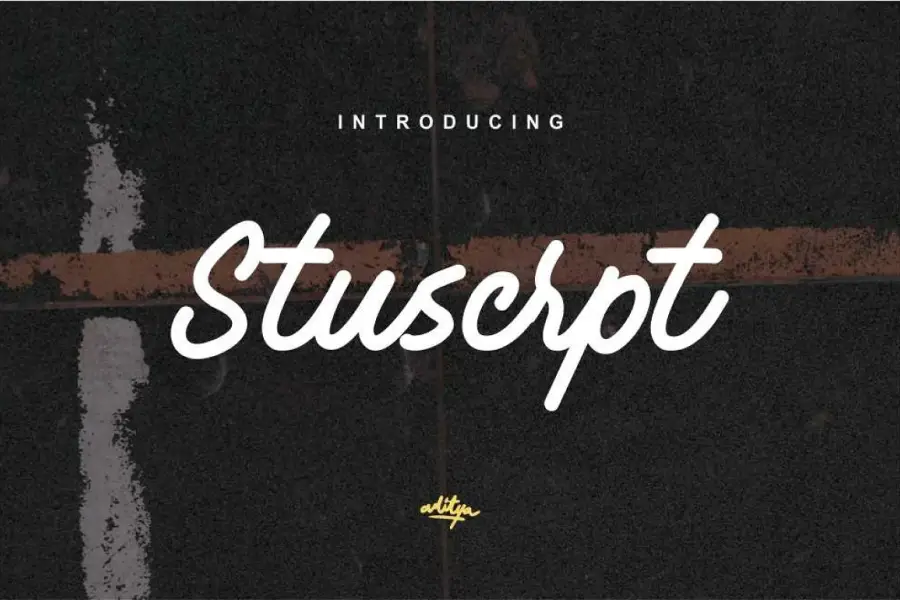
Stuscrpt to nowoczesna czcionka skryptowa, która została wydana w 2020 roku. Ta czcionka może być używana w różnych aplikacjach, takich jak typografia, fotografia i logo. Jego unikalny styl sprawia, że idealnie nadaje się do dodania elegancji Twoim projektom.
Jedną z wyróżniających cech Stuscrpt jest jego wszechstronność. Niezależnie od tego, czy projektujesz logo, czy tworzysz układ typograficzny, ta czcionka z pewnością wyróżni Twoją pracę. Dodatkowo nowoczesny design czcionki gwarantuje, że pozostanie ona aktualna przez wiele lat.
Skrypt Moscato
Moscato Script to urocza i stylowa odręczna czcionka, która dodaje osobistego charakteru każdemu projektowi. Ta czcionka jest wszechstronna i może być używana do różnych zastosowań, takich jak cytaty, plakaty, materiały ślubne, projekty modowe, logo, zaproszenia, artykuły papiernicze i wiele innych.
Unikalne cechy Moscato Script sprawiają, że wyróżnia się on spośród innych czcionek. Ręcznie rysowany wzór nadaje mu naturalny i organiczny charakter, który dodaje charakteru i osobowości Twojej pracy. Jego czyste linie i gładkie krzywe ułatwiają czytanie i doskonale nadają się do dodania odrobiny elegancji do każdego projektu.
Jedną z najlepszych rzeczy w Moscato Script jest jego wszechstronność. Może być używany do szerokiej gamy projektów, od codziennych po oficjalne. Niezależnie od tego, czy projektujesz zaproszenie na ślub przyjaciela, czy tworzysz logo dla nowego przedsięwzięcia biznesowego, Moscato Script sprosta temu zadaniu.
Atakana
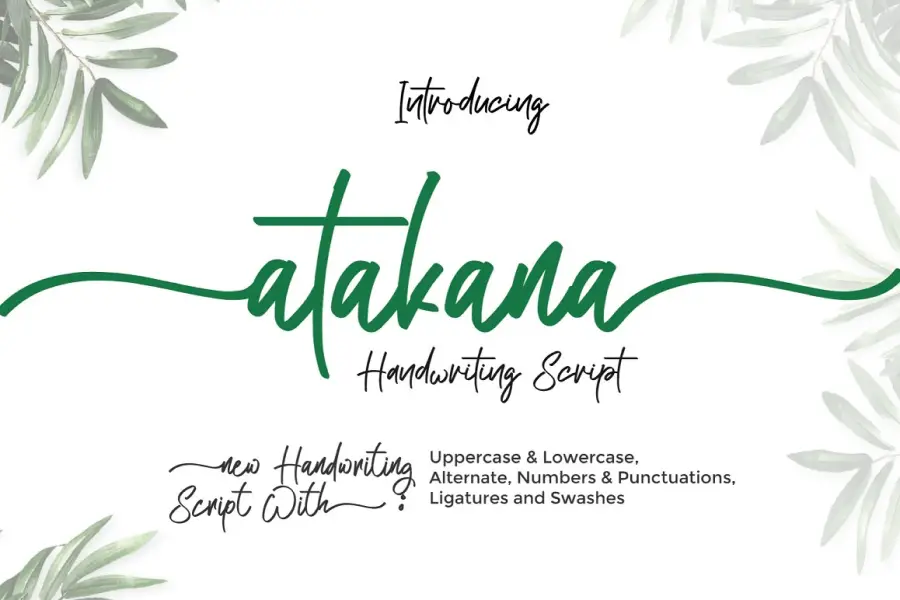
Atakana Script to piękna nowa czcionka pisma odręcznego, która została stworzona z miłością. Jest idealny do wszystkich Twoich potrzeb związanych z brandingiem, niezależnie od tego, czy chodzi o zaproszenia ślubne, romantyczne projekty, marki studyjne, logo, zaproszenia, posty w mediach społecznościowych, odzież, plakaty, znaki kawiarni/restauracji i wiele innych.
Czcionka zawiera eleganckie, wirujące litery, które wyglądają, jakby zostały napisane ręcznie. Jest łatwy do odczytania i dodaje unikalny akcent personalizacji do każdego projektu. Atakana Script nadaje się zarówno do użytku osobistego, jak i komercyjnego, dzięki czemu jest wszechstronną czcionką, której można używać do wszystkiego, od zaproszeń po reklamy.
Czcionka jest dostępna w wielu formatach plików, w tym OTF, TTF i WOFF. Oznacza to, że można go używać na różnych platformach i programach, co czyni go wygodnym wyborem dla projektantów, którzy muszą pracować na wielu urządzeniach.
Scenariusz domku dla ptaków
Skrypt ptaszarni to zachwycająca czcionka odręczna stworzona za pomocą markerów. ta czcionka jest idealna dla osób, które chcą tworzyć charakterystyczne znaki firmowe lub osobiste podpisy i czcionki skryptowe dla słów. zawiera duże standardowe znaki, znaki interpunkcyjne i obsługuje wiele języków.
Unikalny projekt Bird House script nadaje mu zabawny i naturalny charakter, który wyróżnia go spośród innych czcionek. jego ręcznie rysowany wygląd dodaje odrobinę osobowości każdemu projektowi, w którym jest używany. Niezależnie od tego, czy projektujesz logo, czy tworzysz stronę internetową, wszechstronność skryptu birdhouse gwarantuje, że można go używać w różnych ustawieniach.
Florentina
Florentina to czcionka, która może dodać charakteru i wyrafinowania Twoim projektom. Jego projekt skryptu jest idealny do tworzenia logo i brandingu, które wyróżnią się na tle konkurencji. Unikalna kolekcja symboli geometrycznych Florentiny jest również doskonałym dodatkiem do Twojego arsenału projektowego, umożliwiając łatwe tworzenie pięknych i przyciągających wzrok kompozycji.
Elegancki styl pisma czcionki zapewnia klasyczny, a jednocześnie nowoczesny styl, który z pewnością zrobi wrażenie. Jest idealny dla projektantów, którzy chcą dodać odrobinę luksusu do swoich prac, nie rezygnując z czytelności ani funkcjonalności. Niezależnie od tego, czy chodzi o druk, czy projekt cyfrowy, Florentina może przenieść Twoje projekty na wyższy poziom.
Góral
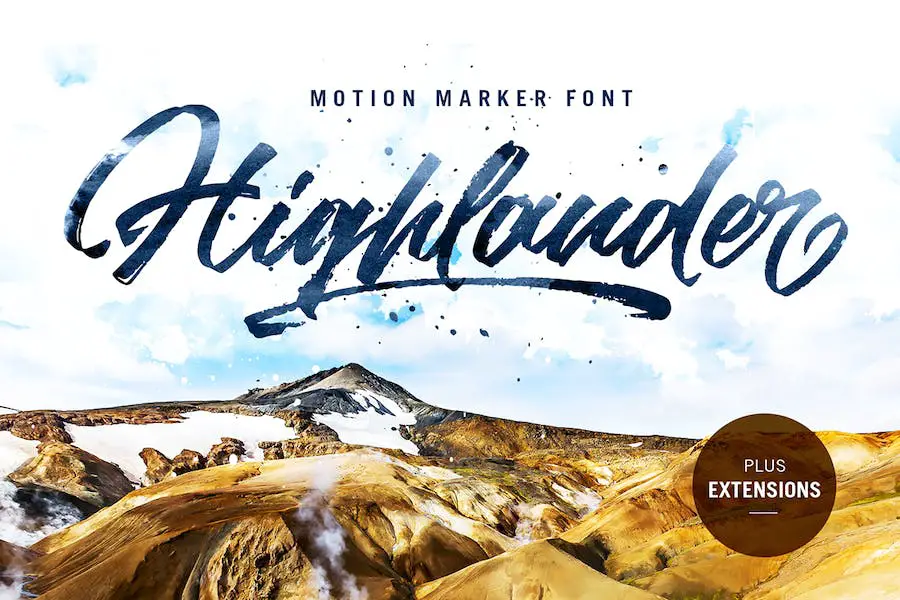
Highlander to obowiązkowa czcionka dla każdego projektanta, który chce tworzyć odręczne litery na zamówienie. Dzięki pełnemu zestawowi wielkich i małych liter ta czcionka zapewnia projektantom swobodę przekształcania tekstu w autentyczne, spersonalizowane dzieła sztuki.
Oprócz standardowych glifów Highlander zawiera również cyfry, znaki interpunkcyjne i obsługę wielu języków. Jako bonus projektanci otrzymają dodatkową czcionkę wypełnioną rozszerzeniami zaprojektowanymi tak, aby idealnie uzupełniały ich główny tekst. Jest również idealny do pogrubionych czcionek skryptowych.
Ogólnie rzecz biorąc, Highlander to doskonały wybór dla projektantów poszukujących wysokiej jakości, wszechstronnej czcionki, która przeniesie ich pracę na wyższy poziom. Niezależnie od tego, czy projektujesz logo, tworzysz plakat, czy projektujesz stronę internetową, zakres funkcji Highlandera sprawia, że jest to doskonała opcja dla wszelkiego rodzaju projektów projektowych.
Pentagon
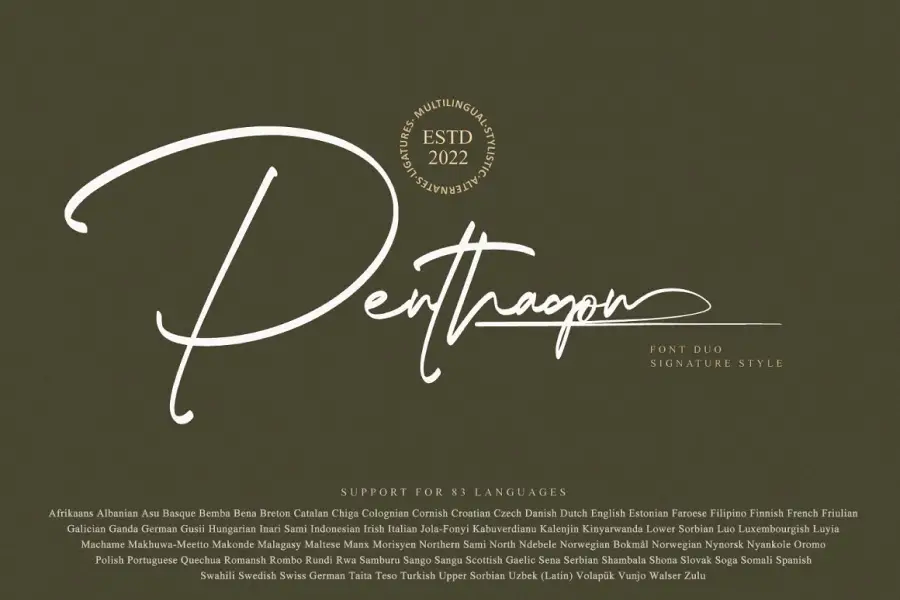
„Penthagon” to duet czcionek skryptowych, który może pomóc w nadaniu produktom biznesowym naturalnego i współczesnego charakteru. Ta elegancka i charakterystyczna czcionka jest idealna do tworzenia odręcznych logo, papeterii ślubnej, logo znaków wodnych fotografów, nowoczesnych stron internetowych, brandingu modowego, wizytówek, zaproszeń ślubnych i innych.
Luksusowy i wysokiej klasy wygląd „Penthagon” wyróżnia go spośród innych czcionek w swojej kategorii. Jego wszechstronność pozwala na wykorzystanie go do różnych projektów, zarówno do użytku osobistego, jak i komercyjnego. Płynne pociągnięcia i naturalne krzywizny każdej litery wydzielają lekką atmosferę, która jest idealna dla każdego projektu. Jest również kompatybilny ze skryptowymi czcionkami ślubnymi.
Skrypt Emelli
Emellie Script to unikalny krój kaligraficzny, który zawiera zabawne kobiece znaki kaligraficzne, dzięki czemu idealnie nadaje się do różnych projektów, takich jak logo, kartki okolicznościowe, materiały ślubne i inne. Ta czcionka zawiera standardowe znaki łacińskie, zamienniki wielkich liter, formy początkowe i końcowe, cyfry i symbole, rozszerzone znaki łacińskie i wybrane ligatury.
Jedną z wyróżniających cech Emellie Script jest jego wszechstronność. Może być używany w szerokiej gamie projektów, od eleganckich po figlarne, i we wszystkich pomiędzy. Początkowa i końcowa forma czcionki oraz wybrane ligatury dodają każdemu projektowi odrobinę personalizacji.
Kolejną wielką zaletą Emellie Script jest to, że zawiera czcionki internetowe. Ułatwia to włączenie czcionki do Twojej witryny, zapewniając spójność na wszystkich platformach.
Podpis rastrowy
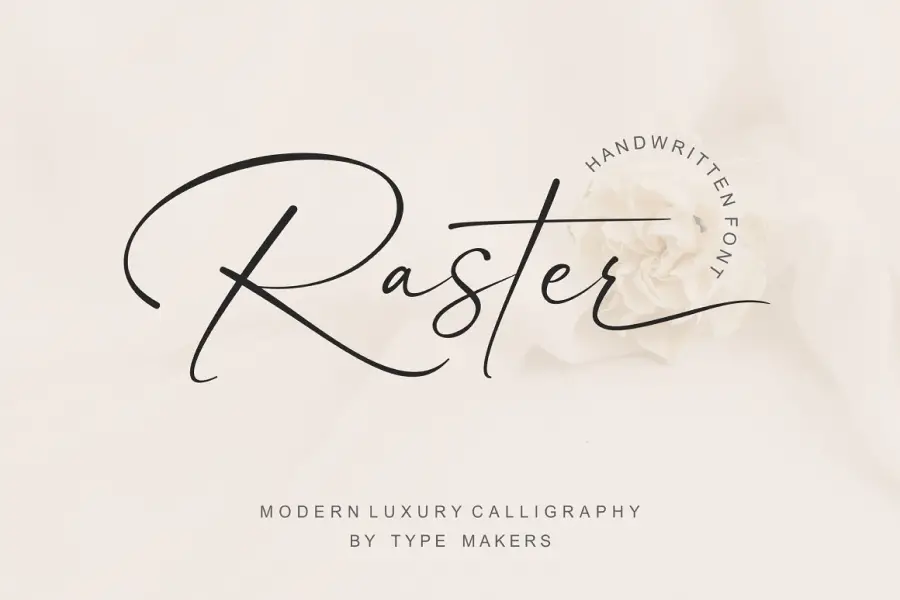
„Raster Signature” to urocza czcionka imitująca naturalne pismo odręczne. Ta czcionka jest idealna do dodawania osobistego charakteru do różnych projektów, w tym logo, zaproszeń, materiałów piśmiennych, projektów ślubnych, postów w mediach społecznościowych, reklam i opakowań produktów.
Dzięki nieregularnym pociągnięciom i delikatnym krzywiznom „Raster Signature” dodaje elegancji i ciepła każdemu projektowi. Ta czcionka jest idealna do tworzenia wyjątkowej i zapadającej w pamięć tożsamości marki, a także do dodawania osobistego charakteru specjalnym wydarzeniom.
Wszechstronność „Raster Signature” sprawia, że jest to doskonały wybór dla projektantów poszukujących czcionki, której można używać w różnych ustawieniach. Od fotograficznych znaków wodnych po etykiety produktów — naturalny urok tej czcionki z pewnością zrobi wrażenie.
Skrypt Rattfiny'ego
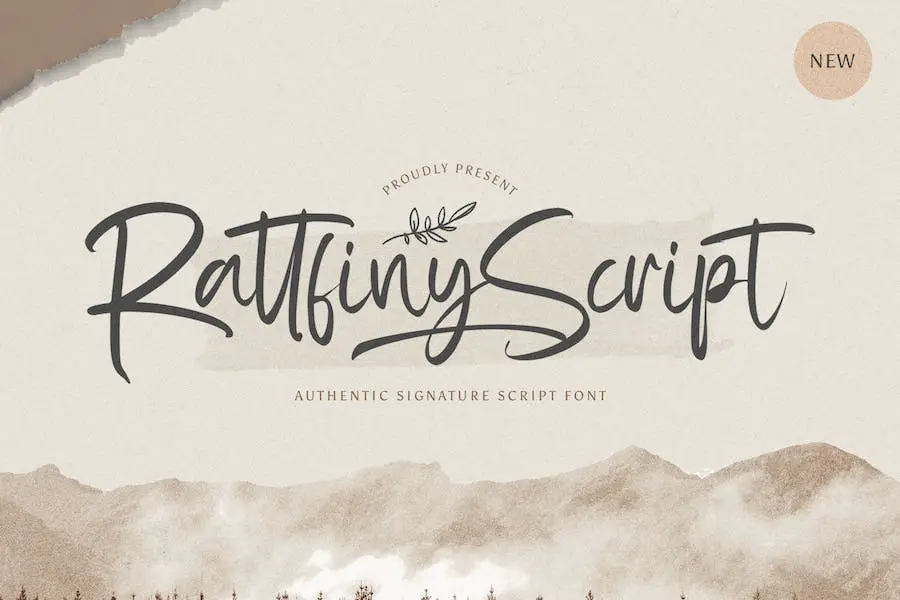
Rattfiny Script to znakomita odręczna czcionka emanująca elegancją i wdziękiem. Jego piękne, płynne postacie są dobrze wyważone, dzięki czemu idealnie pasują do szerokiej gamy projektów. Ta czcionka dodaje odrobinę wyrafinowania każdemu kreatywnemu projektowi, ożywiając go delikatnym stylem pisma.
Jedną z wyróżniających cech Rattfiny Script jest jego wszechstronność. Uzupełnia wiele różnych stylów projektowania, od zaproszeń ślubnych po materiały brandingowe, dzięki czemu jest cennym dodatkiem do każdej kolekcji czcionek. Jej pełne wdzięku krzywizny i skomplikowane detale nadają jej wyjątkowy charakter, który odróżnia ją od innych czcionek skryptowych dostępnych na rynku.
Kolejnym wspaniałym aspektem Rattfiny Script jest jego czytelność. Nawet przy delikatnym wyglądzie litery są łatwe do odczytania, dzięki czemu każda wiadomość, którą przekazujesz za pomocą tej czcionki, będzie wyraźna i czytelna. Niezależnie od tego, czy jest używany w dużych, czy małych rozmiarach, Rattfiny Script zachowuje swoje piękno i wpływ.
Pani Klementyna
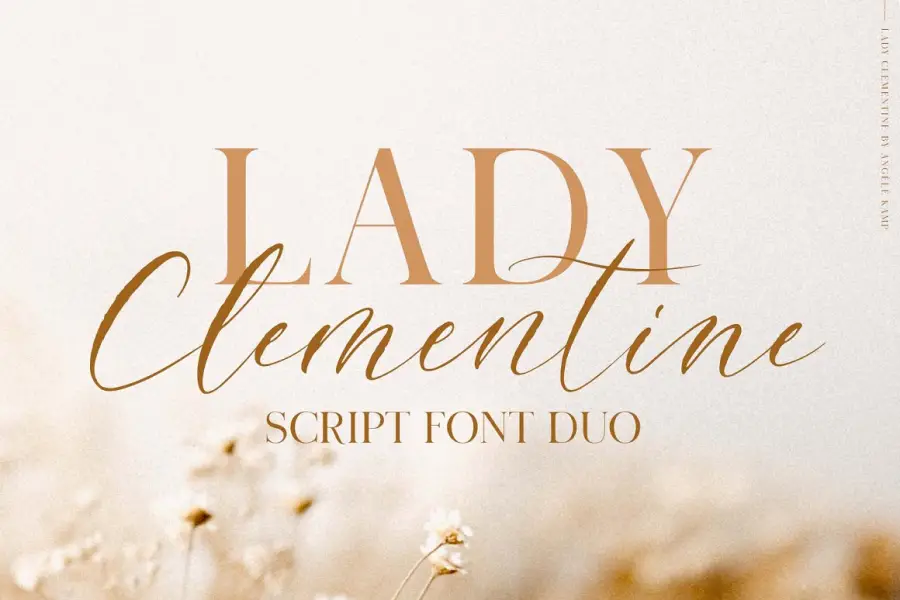
Lady Clementine jest idealnym dodatkiem do kolekcji czcionek każdego grafika. Ten duet czcionek zawiera luksusową czcionkę szeryfową połączoną z piękną czcionką skryptową, która ma odrobinę tekstury, zapewniając autentyczny, nowoczesny wygląd kaligrafii. Jest odpowiedni dla czcionek Google Script.
Elegancki i ponadczasowy design Lady Clementine sprawia, że idealnie nadaje się do różnych zastosowań, takich jak zaproszenia ślubne, kartki z datą, stylowe logo i kobiecy branding. Czcionka szeryfowa doskonale uzupełnia czcionkę skryptową, tworząc równowagę elegancji i stylu, która z pewnością wyróżni Twoje projekty.
Niezależnie od tego, czy projektujesz na oficjalne wydarzenie, czy tworzysz markę z kobiecym akcentem, Lady Clementine to doskonały wybór. Dzięki pięknemu wzornictwu i wszechstronnemu zastosowaniu ten duet czcionek jest niezbędny dla każdego projektanta, który chce dodać elegancji i stylu swojej pracy.
Zofia
Sophitta to wyjątkowa czcionka, którą można wykorzystać do ulepszenia cyfrowych i drukowanych kreatywnych produktów. Ten krój pisma jest idealny do tworzenia plakatów, postów w mediach społecznościowych, brandingu, projektów osobistych i innych projektów, które wymagają stylowego akcentu. Ponadto idealnie nadaje się do czcionek skryptowych dla Figmy.
Sophitta szczyci się stylem scenariusza, który jest elegancko zaokrąglony z nutą figlarnego uroku. Litery płynnie płyną, zapewniając poczucie ruchu i płynności, które przyciągają uwagę i przyciągają wzrok. Jego unikalny, odręczny wygląd dodaje osobowości i charakteru każdemu projektowi, dzięki czemu wyróżnia się z tłumu.
Ta czcionka jest dostępna w różnych stylach, w tym zwykła, pogrubiona, kursywa i pogrubiona kursywa, co daje swobodę wyboru tej, która najlepiej odpowiada potrzebom Twojego projektu. Dzięki wielu dostępnym gramaturom możesz eksperymentować z różnymi kombinacjami, aby stworzyć uderzającą wizualną prezencję.
Centrio
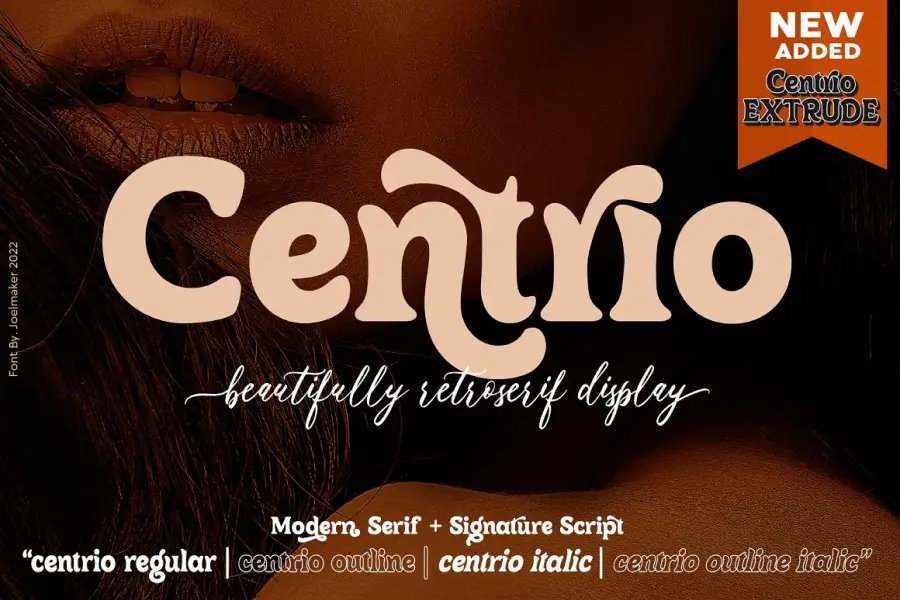
Centrio to unikalny krój pisma w stylu retro, który dodaje artystyczny akcent Twoim projektom. Bezproblemowo łączy nowoczesność z stylem vintage, dzięki czemu idealnie nadaje się do każdego projektu, w którym poszukuje się elegancji i wyrafinowania. Ponadto idealnie nadaje się do czcionek Adobe Script.
Tym, co odróżnia Centrio od innych krojów pisma, jest zastosowanie ligatur i zawijasów, co nadaje mu wyrazisty i przyciągający wzrok wygląd. To sprawia, że idealnie nadaje się do szerokiej gamy projektów, w tym tytułów czasopism, plakatów, logo, koszulek, wizytówek, okładek książek, zaproszeń ślubnych, postów na Instagramie i innych.
Południowy
Southern to nowoczesna i elegancka czcionka skryptowa, która idealnie nadaje się do ślubów, brandingu, logotypów i cytatów. Dzięki pięknym krzywiznom i stylowemu wyglądowi ten krój pisma nadaje wyjątkowy charakter każdemu projektowi.
Jedną z wyróżniających się cech Southern jest wykorzystanie zamaszystych pętli i zawijasów, które tworzą poczucie elegancji i wyrafinowania. Płynne linie czcionki sprawiają, że idealnie nadaje się do wykorzystania w zaproszeniach ślubnych lub innych oficjalnych ogłoszeniach, w których wymagana jest odrobina klasy.
Odręczny styl Southern sprawia, że świetnie nadaje się również do tworzenia logotypów i materiałów brandingowych. Indywidualistyczny charakter czcionki sprawia, że każda marka, która z niej korzysta, wyróżni się z tłumu.
Najlepsze darmowe czcionki skryptowe
W tym artykule przedstawimy niektóre z najlepszych darmowych czcionek skryptowych dostępnych online, wraz z ich funkcjami i linkami do pobrania. Czy wiesz, że czcionki skryptowe należą do najpopularniejszych krojów pisma w projektowaniu? Są znane ze swojego płynnego, odręcznego stylu i mogą przekazywać poczucie kobiecości, intymności i kreatywności. Przy tak wielu opcjach wybór odpowiedniego dla twojego projektu może być przytłaczający.
Ale nie bój się! Przeprowadziliśmy dla Ciebie badania i wybraliśmy śmietankę. Od klasycznej kaligrafii po nowoczesne pismo pędzlem — te czcionki dodadzą Twoim projektom dodatkowego blasku, którego szukałeś. A więc bez zbędnych ceregieli zanurzmy się w świat typografii pisma i odkryjmy niesamowite opcje czcionek.
Jesienne Kwiaty
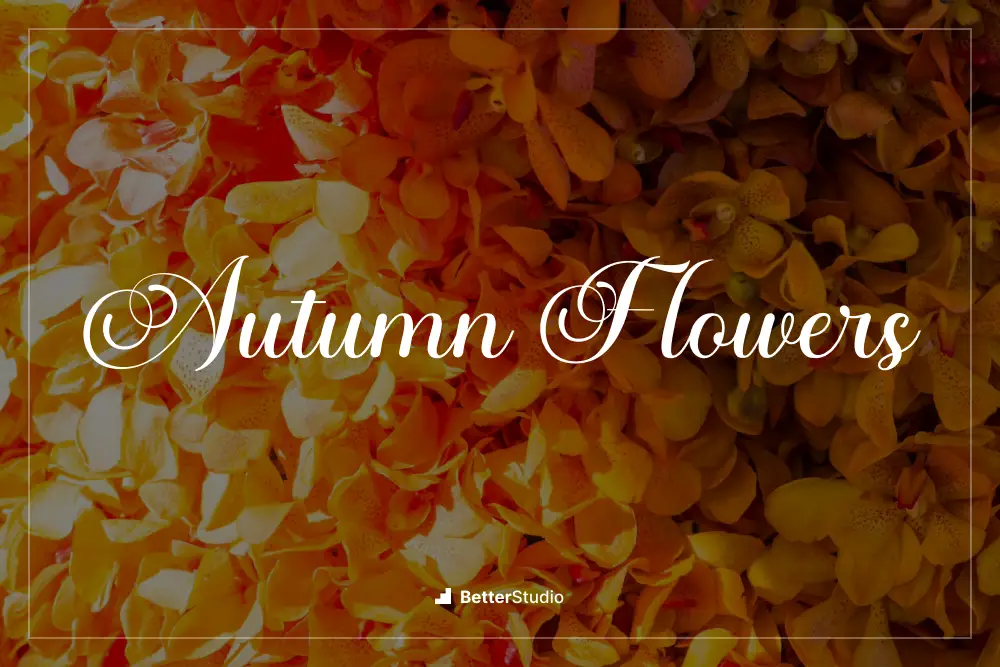
Autumn Flowers to elegancka czcionka pisma kaligraficznego, która dodaje wyrafinowania każdemu projektowi. Dzięki eleganckim krzywiznom i płynnym obrysom ta czcionka jest idealna do tworzenia spersonalizowanych zaproszeń, oznakowań modowych, logo i nie tylko! Ponadto nadaje się do czcionek skryptowych dla obwodu.
Jedną z najlepszych rzeczy w jesiennych kwiatach jest ich wszechstronność. Może być używany w różnych projektach i nadal wygląda niesamowicie. Niezależnie od tego, czy tworzysz zaproszenie na ślub, czy post w mediach społecznościowych, ta czcionka ożywi Twój projekt. Ponadto, ponieważ jest zakodowany w PUA, dostęp do wszystkich glifów i ligatur jest bardzo prosty!
Podpis Darlingtona
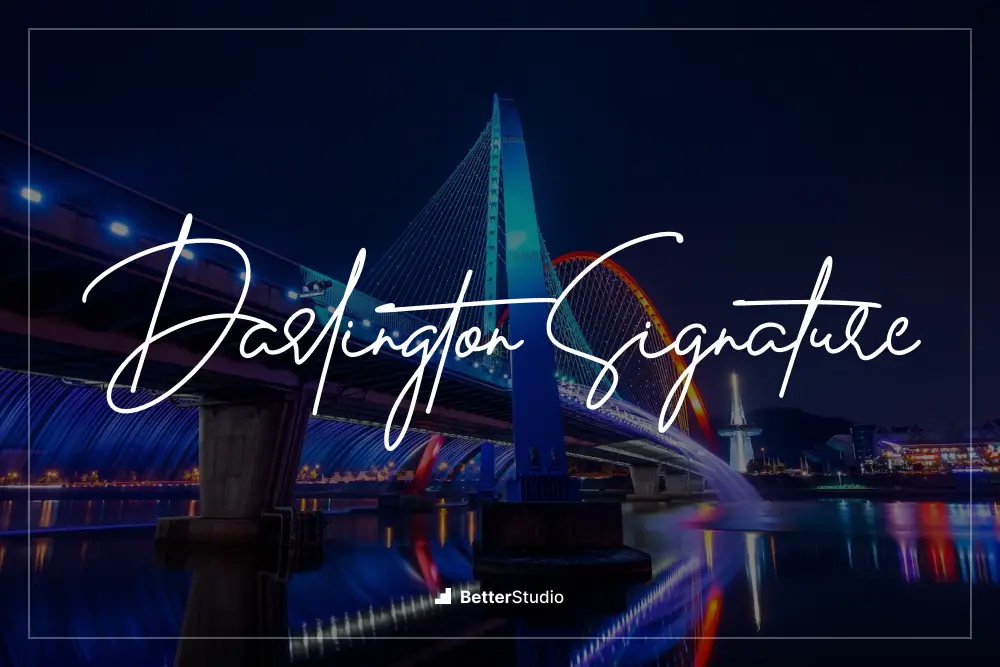
Darlington Signature to czcionka emanująca nowoczesnym stylem i modą. Dzięki eleganckim krzywiznom i wyrafinowanemu wzornictwu ten charakterystyczny krój pisma z pewnością podniesie poziom każdego projektu, w którym jest używany. Jego piękno tkwi w prostocie, dzięki czemu jest idealny dla tych, którzy chcą dyskretnego, ale szykownego wyglądu.
Jedną z najbardziej godnych uwagi cech Darlington Signature jest jego wszechstronność. Może być używany do różnych projektów, od zaproszeń ślubnych po logo i materiały brandingowe. Niepowtarzalny urok czcionki i ponadczasowa elegancja sprawiają, że nadaje się ona na każdą okazję i do każdego celu.
Kolejną wielką zaletą tej czcionki jest jej czytelność. Pomimo fantazyjnego wyglądu, Darlington Signature jest łatwy do odczytania i nie męczy wzroku odbiorców. To sprawia, że jest to praktyczny wybór dla projektów, które wymagają zarówno stylu, jak i funkcjonalności.
Ananda Black
Czcionka Ananda Black to fantastyczny wybór do podkreślania elementów projektu i jest dostępna do pobrania za darmo. Ta czcionka skryptowa ma klasyczny, ale nowoczesny wygląd, który byłby idealny do każdego projektu wymagającego odrobiny elegancji.
Jedną z najbardziej zauważalnych cech Ananda Black są czyste i łatwe do odczytania litery. Gładkie krzywe i ostre krawędzie czcionki sprawiają, że jest ona zarówno przyciągająca wzrok, jak i czytelna. Ponadto wszechstronny styl Ananda Black sprawia, że nadaje się do różnorodnych projektów, od zaproszeń ślubnych po opakowania produktów. Możesz także użyć czcionek skryptowych do tatuaży.
Autan
Auttan to stylowa czcionka do kaligrafii miedziorytowej, która dodaje elegancji i wyrafinowania każdemu projektowi. Dzięki tanecznej linii bazowej i klasycznemu wzornictwu ta czcionka jest idealna do różnych celów, takich jak logo, zaproszenia ślubne, etykiety, wiadomości, plakaty, odznaki i nie tylko.
Jedną z wyróżniających cech Auttan jest jego wszechstronność – można go stosować zarówno we współczesnych, jak i klasycznych projektach, dzięki czemu nadaje się do szerokiej gamy projektów. Odręczny styl czcionki dodaje również osobistego charakteru każdemu tekstowi, dzięki czemu idealnie nadaje się do brandingu i personalizacji Twojej pracy.
Starannie wykonany projekt Auttan zapewnia wysoką czytelność, nawet przy mniejszych rozmiarach. Niezależnie od tego, czy używasz jej na stronie internetowej, czy w druku, ta czcionka zapewni, że Twój tekst będzie łatwy do odczytania i atrakcyjny wizualnie. Dodatkowo, dzięki swojemu unikalnemu stylowi, Auttan z pewnością wyróżni się z tłumu i złoży oświadczenie.
Skrypty
Scriptys to piękna czcionka skryptowa, idealna do użytku osobistego. Jest to rodzaj czcionki, który świetnie nadaje się do tworzenia zaproszeń lub dodawania osobowości do postów w mediach społecznościowych.
Należy pamiętać, że Scriptys jest przeznaczony wyłącznie do użytku osobistego. Jeśli chcesz go używać do celów komercyjnych, musisz przekazać darowiznę twórcy. Ponadto możesz użyć tej czcionki w serwisie Canva.
Ogólnie rzecz biorąc, Scriptys ma wiele wspaniałych funkcji. Czcionka jest łatwa do odczytania, co jest ważne, gdy używasz jej do czegoś takiego jak zaproszenie lub kartka z życzeniami. Ma również zabawny i kapryśny charakter, dzięki czemu idealnie nadaje się do dodawania odrobiny zabawy do twoich projektów.
Klaudia
Claudia Script Font to idealny wybór dla tych, którzy chcą dodać naturalny i stylowy akcent do swojego osobistego brandingu. Jego odręczna czcionka skryptowa nadaje wyjątkowy charakter każdemu projektowi, niezależnie od tego, czy jest to logo, projekt ślubny, czy post w mediach społecznościowych. Wszechstronność Claudii sprawia, że idealnie nadaje się również do pakowania produktów, etykiet, fotograficznych znaków wodnych, zaproszeń i nie tylko.
Naturalny przepływ i styl tego kroju pisma wyróżnia go spośród innych czcionek skryptowych dostępnych na rynku. Jest łatwy do odczytania i przyciąga wzrok, co czyni go doskonałym wyborem dla każdego projektu brandingowego. Smak pisma, który Claudia wnosi do projektu, jest niezrównany, a subtelne krzywizny i linie zachęcają czytelnika do bliższego przyjrzenia się.
Shelly
Shelly to wspaniały nowy skrypt czcionek pisma ręcznego, który idealnie nadaje się do dodania stylu i wyrafinowania do każdego projektu. Ta czcionka, stworzona przez utalentowany zespół Dafont.com, jest nie tylko stylowa, ale także niezwykle łatwa w użyciu.
Jedną z wyróżniających się cech Shelly jest modna i super wyluzowana estetyka. Ta czcionka ma bez wysiłku fajny klimat, który z pewnością zrobi wrażenie na każdym, kto ją zobaczy. Dodatkowo, dzięki seksownym, stylowym dodatkom, Shelly to idealny wybór, jeśli chcesz stworzyć projekt, który naprawdę wyróżni się z tłumu.
Aciluth
Atziluth Script Font to wszechstronny i przyjazny dla użytkownika krój pisma zaprojektowany przez Antona Cahyono. Zawiera ponad 340 glifów z szeroką gamą zamienników, ligatur i znaków kaligraficznych, które dodają finezji projektom brandingu lub logotypów.
Ta czcionka jest oparta na kaligrafii pędzla i emanuje elegancką i kreatywną atmosferą, idealną do różnych celów projektowych, takich jak książki, czasopisma, opakowania, branding i oznakowanie. Mnóstwo alternatyw stylistycznych i kontekstowych ułatwia dostosowanie czcionki do określonych wymagań projektu.
Często Zadawane Pytania
Czcionki skryptowe to rodzaj typografii, który naśladuje pismo odręczne, z płynnymi, kursywnymi pociągnięciami.
Czcionki skryptowe mogą dodać elegancji, osobowości i ludzkiego charakteru Twoim projektom. Są często używane w zaproszeniach, logo i materiałach brandingowych, aby przekazać poczucie wyrafinowania i ciepła.
Weź pod uwagę ton i cel swojego projektu, a także czytelność i czytelność czcionki. Niektóre czcionki skryptowe mogą być zbyt ozdobne lub trudne do odczytania w mniejszych rozmiarach, podczas gdy inne mogą nie pasować do nastroju lub stylu, do którego dążysz.
Ważne jest również przetestowanie czcionki w różnych kontekstach i układach, aby upewnić się, że dobrze pasuje do ogólnego projektu.
Wniosek
Podsumowując, omówiliśmy 24 najlepsze czcionki skryptowe, których możesz użyć w swoich projektach. Każda czcionka ma swój niepowtarzalny styl i osobowość, które mogą dodać uroku każdemu projektowi. Mamy nadzieję, że ten artykuł był pomocny w znalezieniu idealnej czcionki skryptowej do następnego projektu.